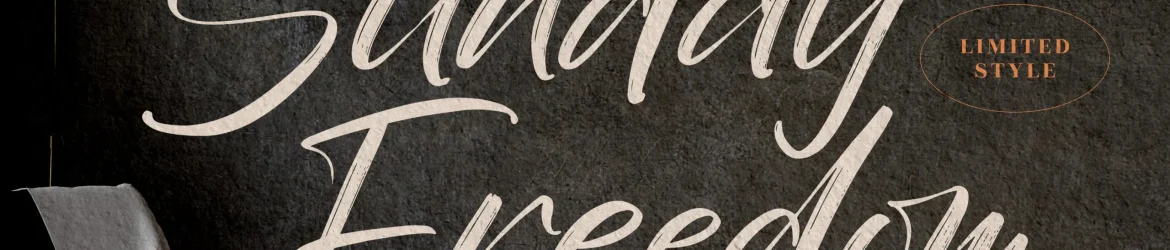
Sunday Freedom Font – Download Grátis
A Fonte ‘Sunday Freedom’ é uma seleção elegante para projetos que precisam de um toque autêntico e vibrante. Através do seu estilo à mão livre, essa fonte permite uma variedade impressionante de aplicações, tornando-a perfeita para criar desde identidades visuais inovadoras até elementos decorativos em mugs ou embalagens de produtos. Seja ela um logo ambicioso, uma capa de livro sofisticada ou um cartão de visita criativo – a ‘Sunday Freedom’ traz o brilho único do desenho manual às suas criações. Com seu design elegante e fluido, essa fonte é ideal para designers que buscam introduzir elementos únicos em qualquer projeto. Perfeita para projetos de identidade visual, ‘Sunday Freedom’ oferece um toque delicado e atemporal que pode tornar a sua marca ainda mais memorável. Além disso, seu uso na publicidade, como em cartões de visita ou capas de livros, proporciona um acabamento autêntico que se destaca. Não hesite em explorar os inúmeros possíveis usos dessa fonte de brushed à mão livre para suas criações – ‘Sunday Freedom’ está aqui para dar vida e personalidade a todos os seus projetos.